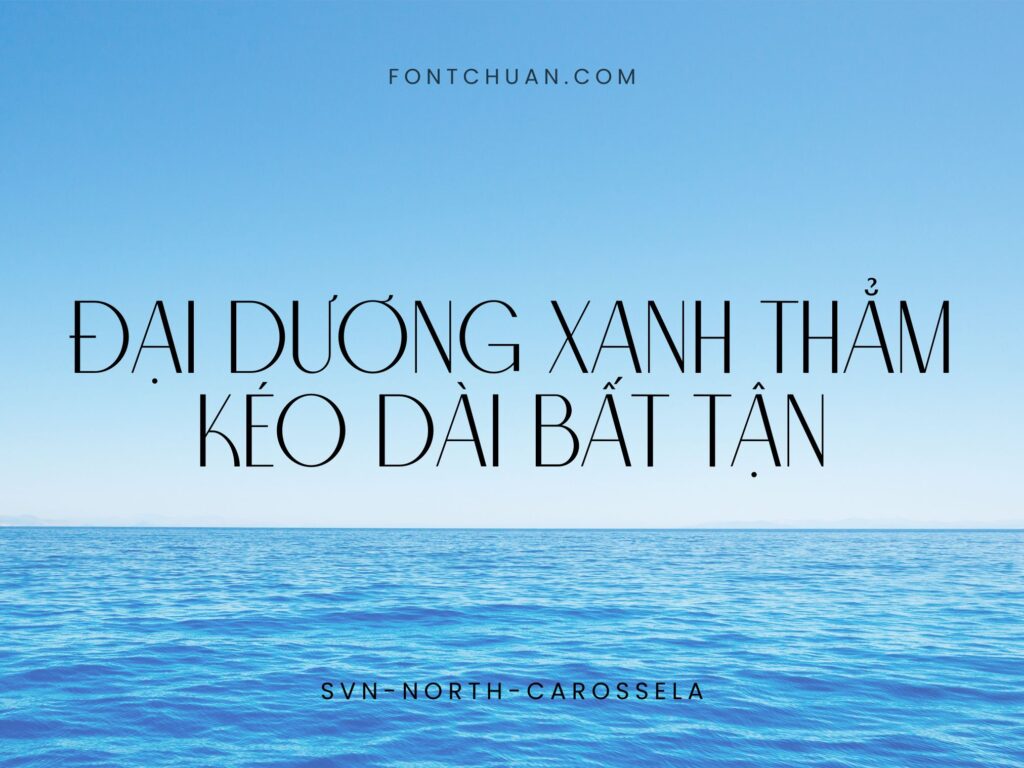
Font SVN North Carossela là phiên bản Việt hóa của kiểu chữ North Carossela, được thực hiện bởi STYLEno.1 Fonts. North Carossela là một kiểu chữ sans-serif thanh lịch và hiện đại, được thiết kế bởi Ahmad Sidiq và phát hành bởi BrandSemut. Font này nổi bật với các ligature độc đáo và các ký tự thay thế, mang đến sự tinh tế và phong cách cho thiết kế. North Carossela bao gồm đầy đủ các ký tự chữ hoa, chữ thường, chữ số và dấu câu, hỗ trợ đa ngôn ngữ. Font này phù hợp cho nhiều mục đích sử dụng khác nhau như thiết kế logo, tiêu đề tạp chí, bao bì sản phẩm và các ấn phẩm truyền thông. ([STYLEno.1 Fonts](https://www.svnfont.com/viet-hoa-svn-north-carossela/))
SVN North Carossela lý tưởng cho các dự án thiết kế yêu cầu sự thanh lịch và hiện đại, như thiết kế logo thương hiệu, tiêu đề tạp chí thời trang, bao bì sản phẩm mỹ phẩm và các ấn phẩm truyền thông liên quan đến lĩnh vực thời trang và làm đẹp. Các ngành nghề như quảng cáo, bất động sản và giáo dục cũng có thể tận dụng font này để tạo điểm nhấn trong thiết kế. Ngoài ra, font cũng thích hợp cho các sự kiện như Tết, Giáng sinh, Valentine và các lễ hội khác.